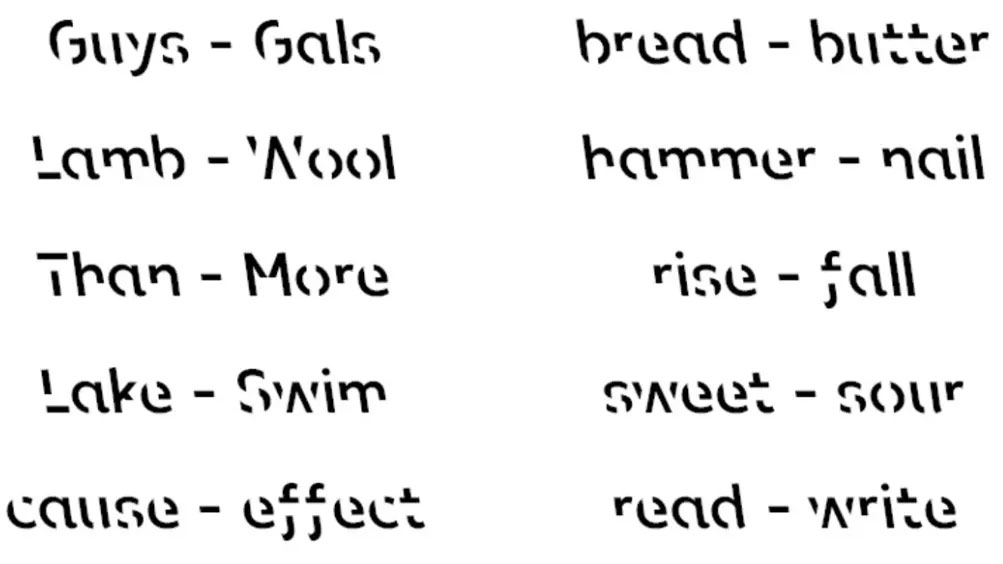
Sans Forgetica
Автор – Lan Huang
Авторы разработки из университета RMIT в Мельбурне, Австралия, назвали свое детище «Sans Forgetica». Это первый в мире шрифт, который позволяет быстрее и точнее вспоминать прочитанное. Все дело в комбинации пустых мест в написании букв – оно подобрано таким образом, чтобы не утомлять мозг, а стимулировать его.
В образовательной системе есть концепция «полезного затруднения», которая используется для усложнения выполнения обычных заданий. Это заставляет ученика отказаться от шаблонного мышления, действовать творчески и лучше усваивать новую информацию. Недавно был создан шрифт, который сам по себе является «полезным затруднением» и помогает тренировать память учеников.
Если текст написан одинаковым шрифтом, он сливается в единый «массив», и мозгу тяжело вычленить смысл из букв. Если шрифты разные, внимание тратится на то, чтобы разобраться между ними и уловить общий смысл. А Sans Forgetica стал своего рода золотой серединой — он достаточно разборчив, но в то же время заставляет мозг подключаться, чтобы уловить смысл. Эффективность подхода проверена и доказана на сотнях первокурсников университета.
Для проверки эффективности было проведено исследование, в котором поучаствовало 400 студентов. Их разделили на две группы и дали почитать два варианта одинакового текста: один написан шрифтом Sans Forgetica, а другой — Arial. Текст, напечатанный шрифтом Sans Forgetica запомнился студентам на 57%, тогда как текст со шрифтом Arial — только на 50%.
Dr Janneke Blijlevens and Dr Jo Peryman (nee Laban) from RMIT’s Behavioural Business Lab in-formed the design of Sans Forgetica using principles of cognitive psychology. They collaborated with the School of Design to produce a typeface specifically designed to enhance memory reten-tion.
Stephen Banham is a lecturer of typography at RMIT University’s School of Design. He collaborat-ed with the Behavioural Business Lab to design a font using psychological principles to enhance memory retention.